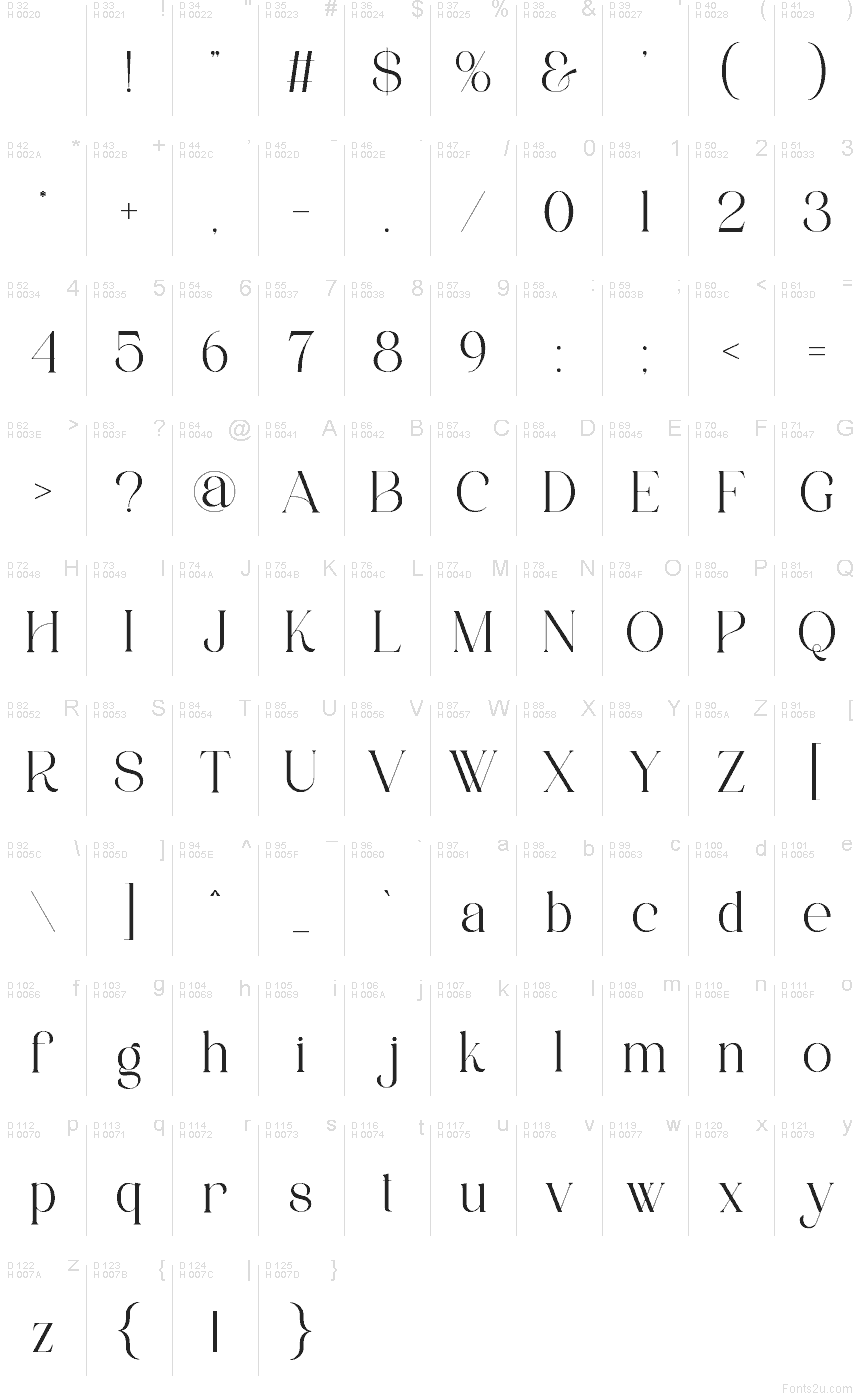
Achilo es una tipografía serif editorial de alto contraste, gratuita y diseñada por Ermedia Studio, que aporta ese estilo elegante propio de las revistas de moda de 2025. Sus letras combinan trazos finos con verticales marcadas, mientras que sus curvas generosas le otorgan un aire refinado, alejándose de lo rígido.
Esta fuente gratuita es ideal para branding de lujo, packaging de cosmética, cabeceras de revistas, etiquetas de perfumes, portadas de libros y títulos cortos. Su contraste sofisticado dota a nombres, líneas de portada y monogramas de una presencia serena y exclusiva.